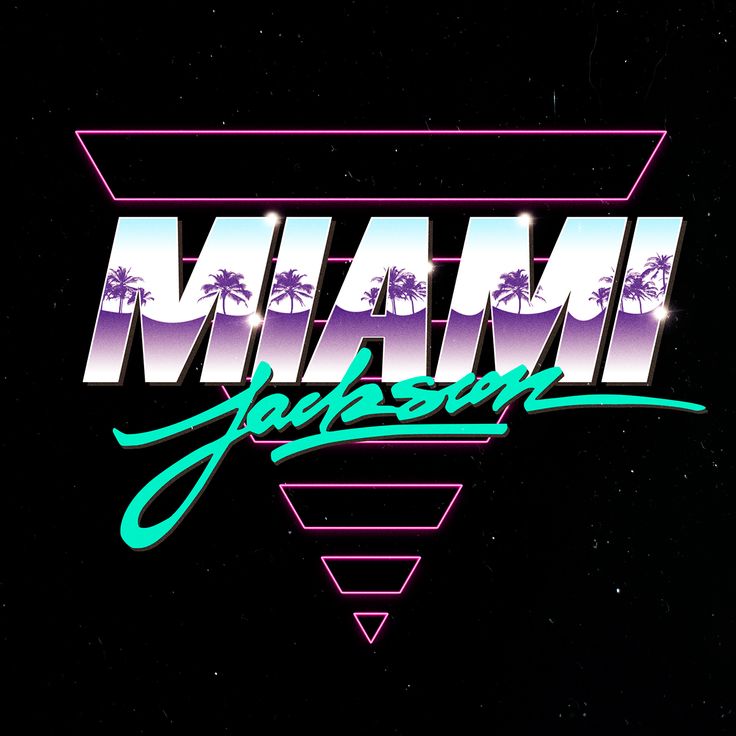
Гарнитуры 80-х: использование, характеристики и лучшие образцы
80-е были десятилетием, полным винтажной одежды и большого количества ретро-дизайна. Десятилетие, которое никогда не вернется, но, тем не менее, современная мода и дизайн объединились, чтобы вернуться в те годы ярких красок и жизни.
Но на этот раз мы хотим поговорить с вами не о моде, а об одном из наиболее часто используемых элементов графического дизайна — типографике. Так мы принесли вам раздел, где покажем одни из лучших ретро-шрифтов 80-х, чтобы вы могли создавать свои проекты как можно более винтажно.
Кроме того, мы объясним некоторые характеристики этого дизайна шрифта.
Гарнитуры 80-х: Дизайн и характеристики
Шрифты 80-х, также известные как ретро-шрифты, это стиль шрифтов, который был очень влиятельным в 80-х годах и в эпоху, которую мы также знаем как винтаж.
Это очень выразительные шрифты, наполненные очень яркими и разнообразными цветами. Так что, если персонаж говорит о них, подразумевается, что это шрифты, которые показывают живой и веселый характер.
Хотя многие из нас не верят в это, эти шрифты сопровождали на протяжении всей истории, для многочисленных брендов, а также были главными героями многих рекламных роликов. Несомненно, деталь, которая во многом их характеризует, заключается в том, что они обычно имеют довольно раскрепощенные и широкие формы, что еще больше способствует их индивидуальности и творчеству.
Короче говоря, всякий раз, когда мы имеем дело с винтажным или ретро-элементом, означает, что это происходит из 80-х или даже 70-х годов, поэтому они являются элементами, которые сохраняются в мировой истории, и в этом случае также ст.
Ниже мы покажем вам некоторые простые характеристики этого типа шрифта и его характерный и уникальный дизайн.
общие черты
- Хотя это правда, что шрифты в стиле ретро или 80-х имеют долгую историю
, никогда нельзя классифицировать как старые гарнитуры или шрифты. Мир искусства обширен и очень длинен, но мы считаем старым все, что предшествует многим известным нам изобретениям, являющимся частью XIX века. - Это тип источников, которые, несмотря на многолетнее использование, все еще используются. Так что они являются частью графического дизайна, который мы также знаем сегодня. На самом деле, все больше и больше брендов делают ставку на этот тип дизайна в своем дизайне.
- Существуют различные типы винтажных шрифтов или шрифтов 80-х годов, поэтому мы находим все больше и больше дизайнов на интернет-страницах и сайтах. Они очень разнообразны и разнообразны среди них.
- Среди его особенностей такжеe подчеркивает, что это шрифты, которым удается привлечь внимание публики, своей формой и своей выразительностью.
Однако они не только имеют эту функциональность в качестве основного эталона, но и сохраняют очень характерную толщину в своих формах. Аспект, который со временем рассеивался, пока не нашел ретро или винтажные шрифты с очень современными графическими деталями, типичными для сегодняшнего дня.
Примеры шрифтов из 80-х
Рен
На первый взгляд типографика Рен может показаться далекой от того, что мы знаем как ретро или винтажные времена. Но если мы поработаем с ней, мы увидим, что помимо ее старого западного стиля она также присутствует в своем дизайне, небольшие вариации, характерные для 80-х.
Инновационный шрифт, с помощью которого вы можете комбинировать разные стили, выходящие за рамки ковбойской стороны старого запада. Он характеризуется тем, что содержит до четырех совершенно разных стилей между ними. Кроме того, он не только становится одним из самых разнообразных и креативных шрифтов, но он также имеет определенную игру и предлагает отличное качество для ваших проектов.
Он доступен на некоторых из самых необычных интернет-страниц для загрузки шрифтов или шрифтов этого стиля. Кроме того, он также характеризуется тем, что является очень подходящим шрифтом для больших заголовков, что облегчит вам его использование в некоторых средствах массовой информации, таких как плакаты, рекламные ролики или крупные бренды. Не стесняйтесь попробовать, так как это очень необычный шрифт среди существующих с такой же типологией.
Дерзайте и пробуйте разные стили и разные модальности.
Macna
Шрифт: Шрифты Cufon
Добро пожаловать и добро пожаловать в мир ар-деко. Без сомнения, мы представляем вам один из тех шрифтов, которые любят все мы, поклонники искусства. и его история, его эволюция, его представление и его уникальный и особый характер.
Macna — это шрифт, который на первый взгляд переносит вас в одно из самых выдающихся художественных направлений в мире искусства — ар-деко. Шрифт, который не только представляет некоторые истории из 80-х, но и 20-е, с индивидуальностью, которая лишит вас дара речи.
Заключительные мысли о шрифтах 80-х
В дизайнерской коллекции шрифтов важно иметь широкий диапазон стилей. Шрифты 80-х значительно добавляют творческих дизайнерских проектов. От ретро-футуристических шрифтов до дикого дизайна букв — шрифты 80-х создают настроение, как никакое другое десятилетие.